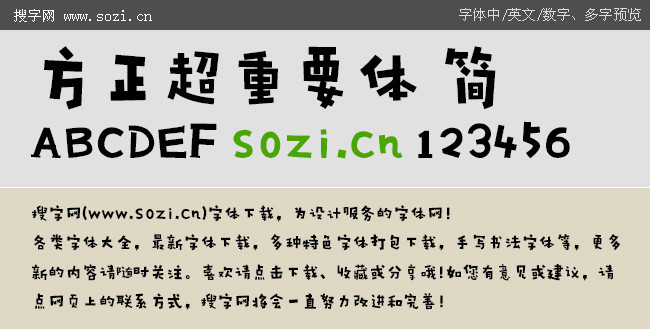
方正超重要體-簡(jiǎn)
搜字網(wǎng)提供一款方正超重要體-簡(jiǎn)中文藝術(shù)字體下載,這款字體筆觸粗實(shí),具有很強(qiáng)的視覺(jué)感染力,看上去有種笨重的感覺(jué),適合應(yīng)用于廣告設(shè)計(jì)、名片設(shè)計(jì)、藝術(shù)設(shè)計(jì)、平面宣傳設(shè)計(jì)、產(chǎn)品設(shè)計(jì),信箋明信片應(yīng)用、包裝印刷等領(lǐng)域。